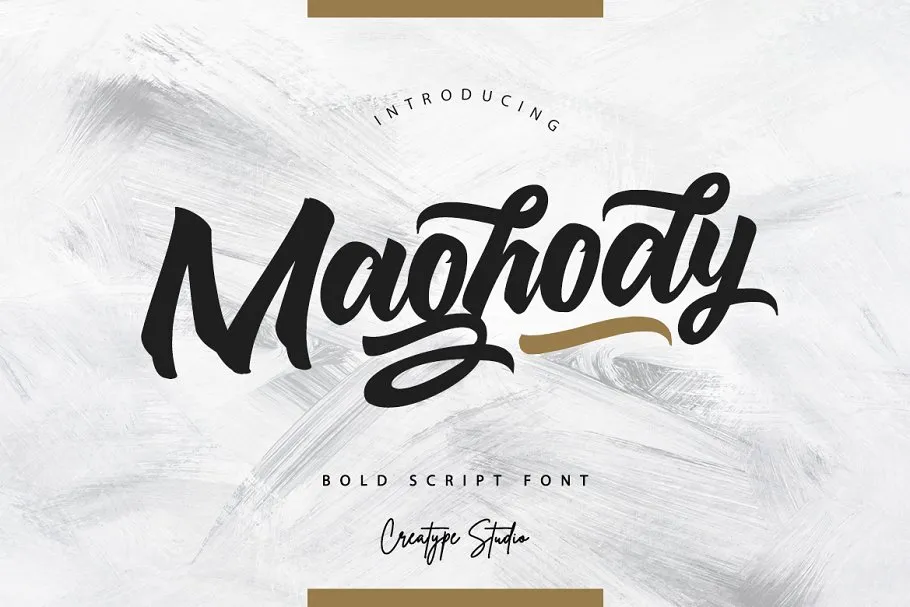
Esta é uma forte tipografia script com movimento círculo acentuado. Foi criada para auxiliar os designers a combinar e incorporar as fontes nas suas criações. Introduzimos a Maghody tipo-font, desenvolvida pela Wacaksara Co. Esta maghody typeface é um tipo de letra script com estilo forte e movimento natural. Ideal para projetos diversos e incríveis – como logotipos e marca, convites, estacionários, designs nupcionais, postagens nas redes sociais, anúncios, embalagens de produtos, design dos produtos, etiquetas, fotografia ou marcas especiais. Esta maghody fonte é perfeita para um vasto conjunto de projetos, tanto corporativos quanto pessoais. É uma escolha ótima para designers em busca de criar expressões distintivas e impactantes na sua comunicação visual.